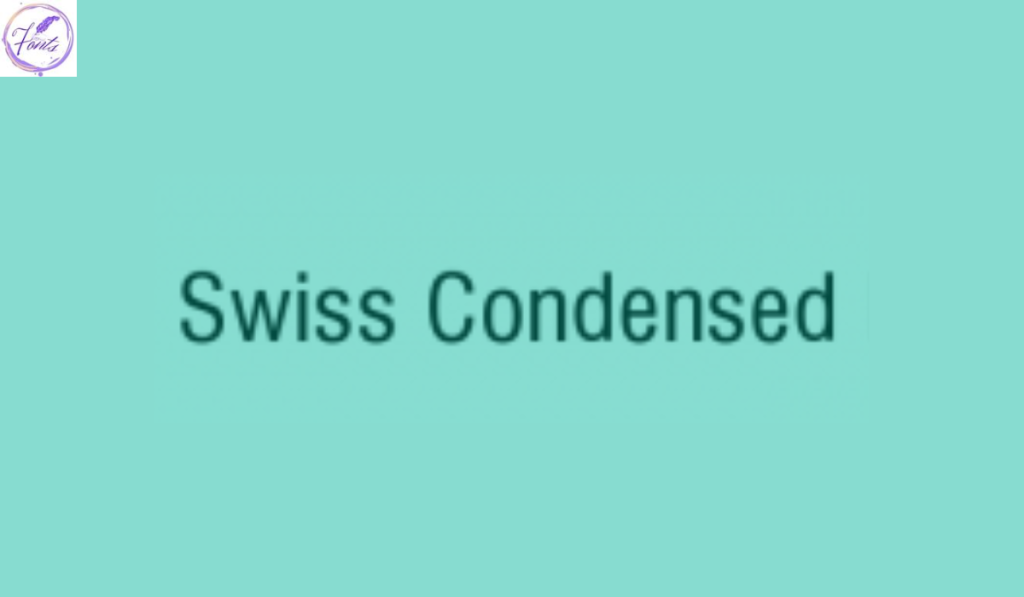
Font Swiss Condensed việt hóa
Tác giả: Bitstream
Bộ Font: Swiss 721 Condensed
Phân loại: Cá tính, độc đáo
Kiểu chữ: Kiểu chữ không chân
Độ dày: Thin, Light, Regular, Medium, Bold
Font swiss condensed là một trong những phông chữ được yêu thích nhất bởi tính thẩm mỹ và sự tiện dụng mà nó mang lại. Được phát triển bởi Bitstream vào năm 2014, phông chữ này đã nhanh chóng chiếm được cảm tình của các nhà thiết kế đồ họa trên toàn thế giới. Với kiểu dáng gọn gàng, thanh lịch, font swiss condensed không chỉ giúp tăng tính chuyên nghiệp cho dự án của bạn mà còn tạo sự dễ đọc, dễ hiểu cho người xem. Font này đặc biệt phù hợp cho các tiêu đề, biển quảng cáo và các tài liệu in ấn yêu cầu tính thẩm mỹ cao.
Đánh giá font swiss condensed
Font swiss condensed nhận được nhiều lời khen ngợi từ cộng đồng thiết kế. Sự hài hòa giữa các ký tự và khoảng cách giữa các chữ cái được đánh giá rất cao. Người dùng thường cảm nhận rằng, font này giúp cho văn bản trông gọn gàng và dễ đọc hơn. Không chỉ vậy, font swiss condensed còn rất linh hoạt trong việc áp dụng cho nhiều loại dự án khác nhau, từ thiết kế website, ấn phẩm in ấn, cho đến các sản phẩm kỹ thuật số. Đặc biệt, với phiên bản việt hóa, font này đã đáp ứng hoàn hảo nhu cầu sử dụng trong ngôn ngữ tiếng Việt mà không gặp bất kỳ trở ngại nào về mặt kỹ thuật.